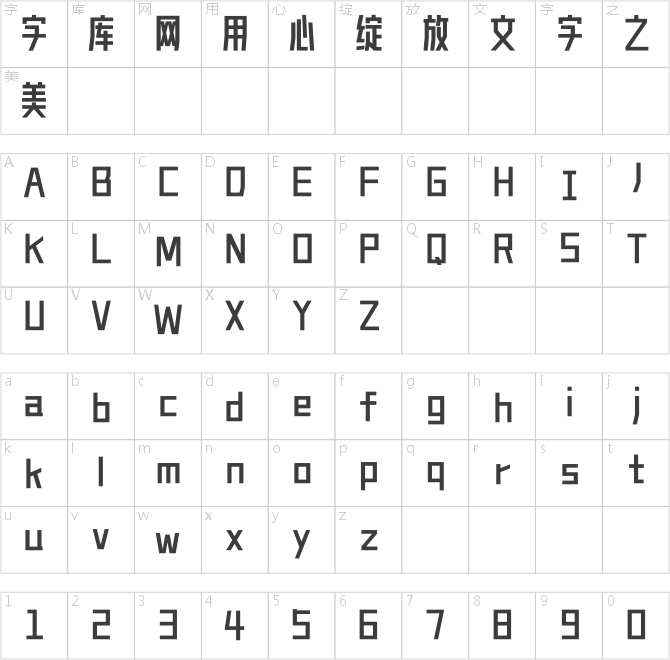
字体名称: 造字工房体
造字工房体
造字工房体介绍
造字工房体系列字形修长,潇洒畅快,给人以通达之感;笔画纵横有象,潇洒淋漓,架构挺拔劲健、布白通透,舒展挺健信然有力,尽显畅远通达的律动之美。适用于大标题及个性品牌设计推广等环境。本字体为简体字库,采用OpenType/CID格式,Adobe-GB1-5编码。基于中华人民共和国GB2312-80字符集标准,另按需添加101个汉字。共收容字数6864CJK汉字,ASCII常用字符100个。